Bagi seorang desainer, mengoleksi berbagai jenis font adalah satu hal yang wajib dilakukan. Salah satu jenis yang wajib dimiliki adalah font tegak bersambung. Font ini memiliki banyak kegunaan, contohnya seperti untuk membuat desain undangan pernikahan, ucapan natal, kaligrafi, acara kesenian dan sebagainya. Selain itu, font ini juga biasa dipakai untuk membuat kata-kata pada mockup, hingga konten.
Tapi kalau Anda bingung mencari font tegak bersambung yang pas untuk desain, jangan khawatir. Karena di sini telah kami sediakan beragam font tegak bersambung keren dan gratis yang dapat Anda download. Mulai dari font tegak bersambung tipis, tebal, kreatif dan unik tersedia di sini. Ini dia daftar rekomendasi font tegak bersambung keren, aesthetic dan gratis yang cocok untuk desain Anda.
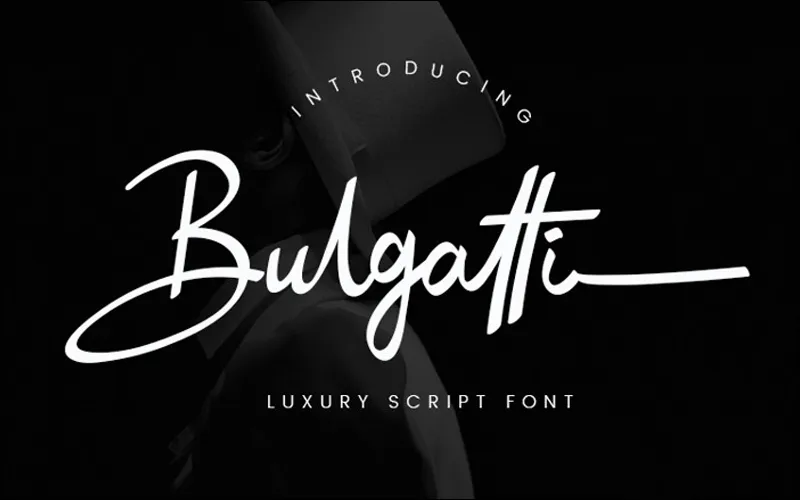
Bulgatti adalah font tegak bersambung kekinian dengan desain yang terlihat mahal. Font ini memiliki ukuran yang cukup tebal, sehingga cocok digunakan untuk membuat desain apa pun. Namun sangat cocok dipakai untuk membuat poster acara VIP.
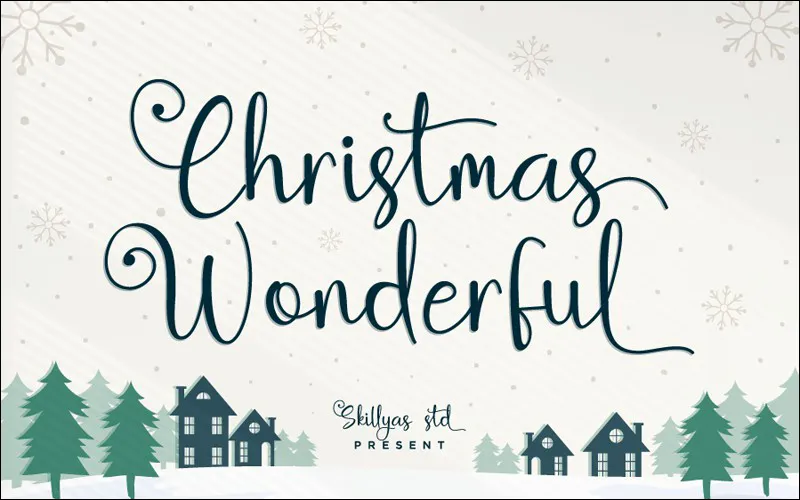
Sesuai dengan namanya, font Christmas Wonderful ini cocok dipilih untuk membuat desain bertema natal. Jadi kalau kamu ingin membuat kartu ucapan natal, poster, konten dan lainnya yang bertema natal disarankan menggunakan font Chrisftmas Wonderful ini.
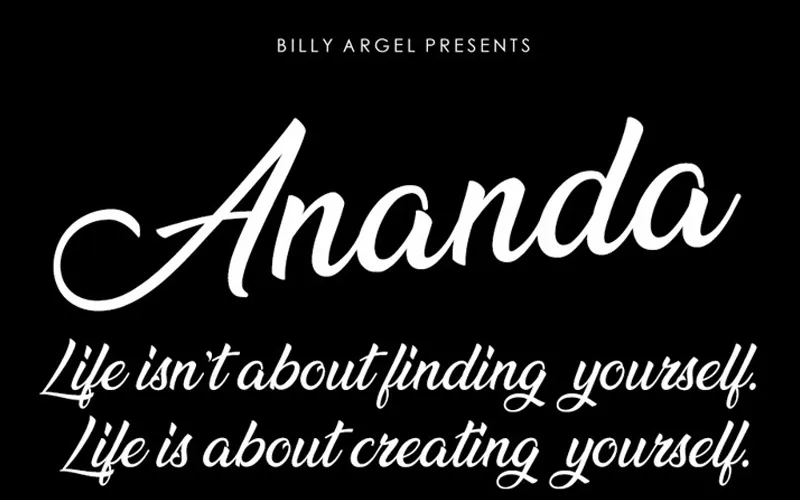
Ananda Black adalah font yang cocok Anda gunakan untuk membuat judul di dalam desain. Alasannya, karena font ini tidak terlalu terlihat menyambung, sehingga bisa mudah dibaca oleh orang lain yang melihatnya.
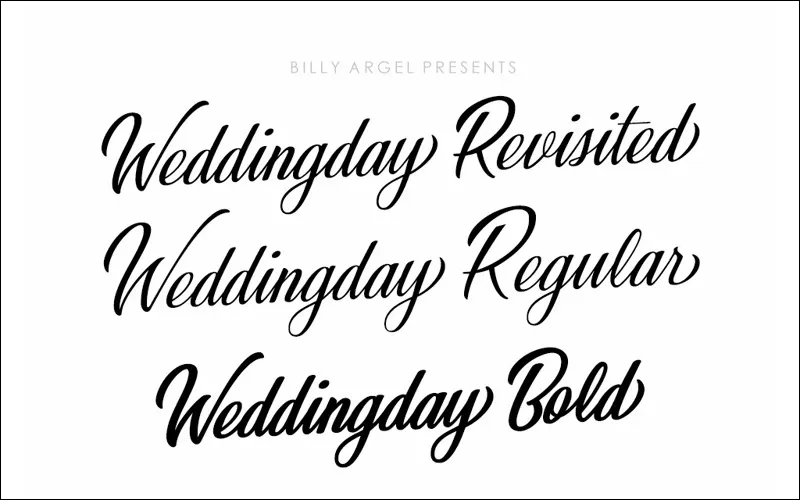
Undangan pernikahan biasanya menggunakan font tegak bersambung supaya terlihat cantik. Salah satu font tegak bersambung yang kami sarankan untuk desain tersebut adalah Wedding Day. Di mana font ini terlihat simpel, sehingga mudah untuk dibaca.
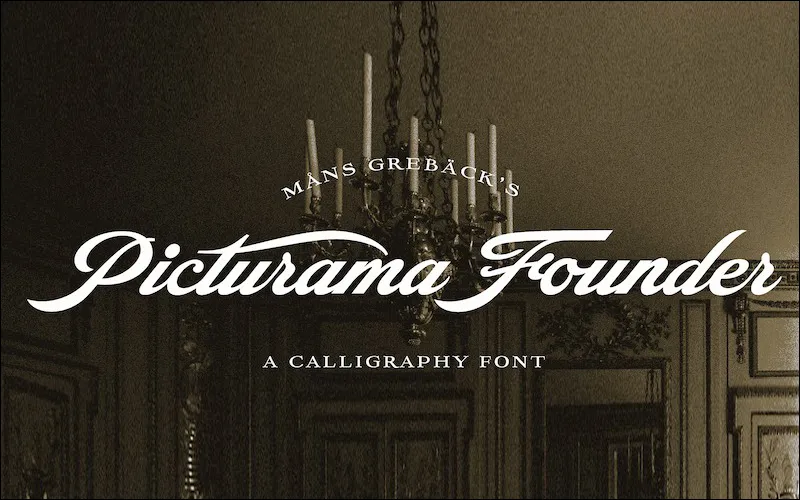
Picturama Founder merupakan salah satu font tegak bersambung yang terlihat mahal. Dari bentuknya yang miring, font ini bisa Anda gunakan untuk membuat desain logo aesthetic.
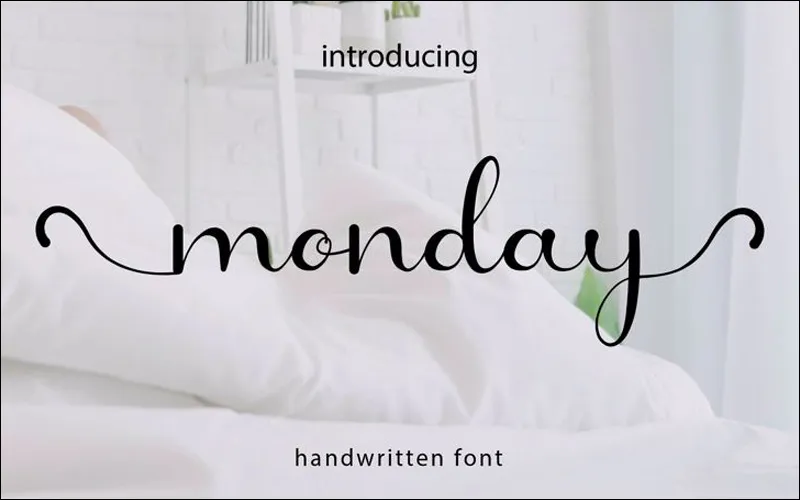
Bagi Anda seorang kreator, font Monday bisa menjadi pilihan untuk membuat desain kreatif. Umumnya, font ini sering dipilih oleh kreator perempuan, karena punya karakter yang cantik.
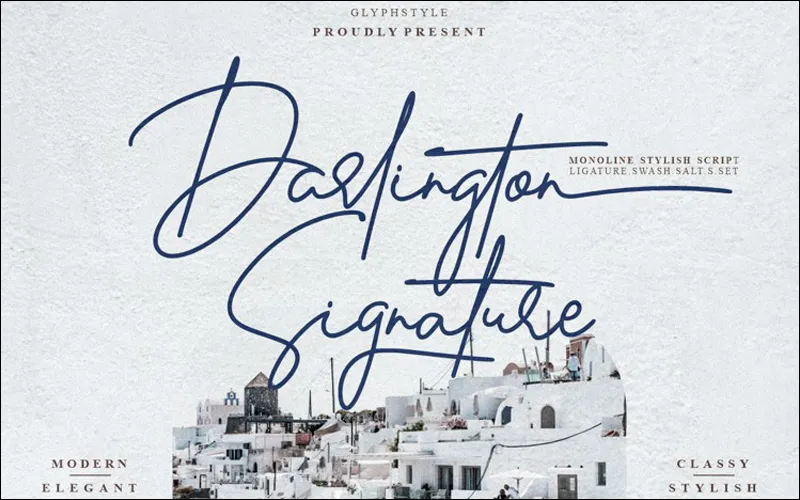
Sedangkan kalau Anda menyukai teks dengan bentuk mirip tanda tangan, maka bisa menggunakan Darlington Signature. Font ini memiliki karakter tipis dan kaku, mirip seperti tanda tangan.
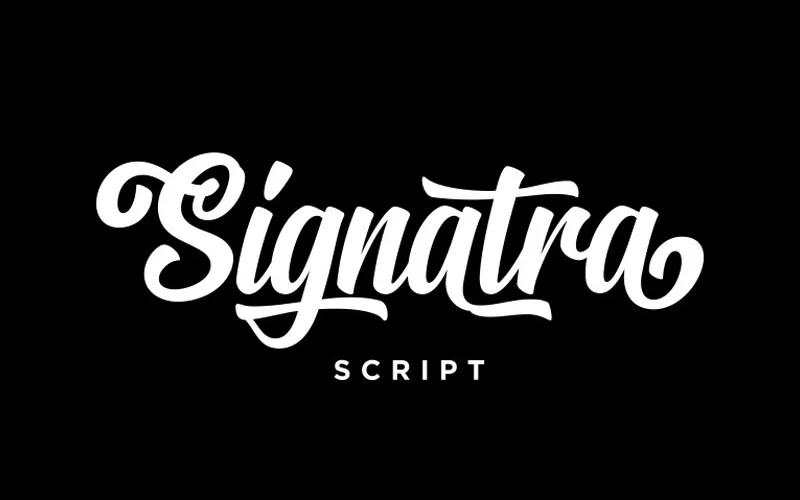
Sedangkan kalau ingin font tegak bersambung mirip tanda tangan namun punya karakter tebal, bisa pakai Signatra. Biasanya font ini sering dipakai juga untuk membuat judul di desain apa pun.
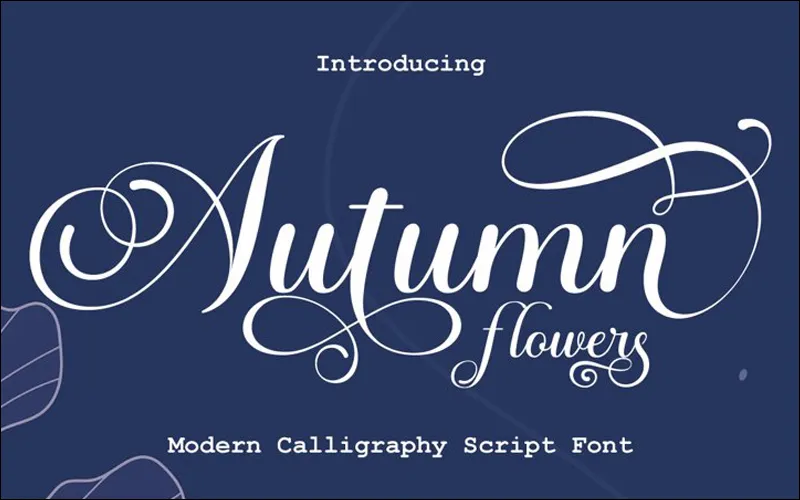
Autumn Flower adalah font tegak bersambung modern yang cukup sering digunakan untuk membuat beragam desain. Mulai dari desain undangan pernikahan, acara ulang tahun, poster kesenian dan sebagainya.
Emotional Rescue adalah font tegak bersambung yang punya desain kursif. Di mana, setiap karakter di font ini di desain menyambung dengan bentuk yang cenderung mengalir. Mirip seperti tulisan tangan.
Kalau kamu sedang membuat desain yang bertema keuangan, Billions Dream bisa menjadi pilihan. Font ini biasa dipakai untuk membuat judul buku finansial.
Stylish Calligraphy adalah font tegak bersambung yang mengusung tema kaligrafi. Font ini bisa digunakan untuk membuat desain apa pun. Lebih cantik lagi, jika Anda bisa memadukan warna yang pas.
Font undangan pernikahan sedang banyak dicari belakangan ini. Di tambah adanya undangan digital. Salah satu font untuk membuat desain undangan yang bisa Anda pilih adalah Geraldine. Bentuknya yang cantik, di tambah riasan bunga di beberapa karakter membuat font ini sangat direkomendasikan untuk dipilih.
Cherolina adalah font tegak bersambung yang punya indent panjang. Meskipun begitu, font ini punya desain yang elegan dan mewah sehingga cocok digunakan untuk membuat apa pun.
Font tegak bersambung untuk membuat judul selanjutnya adalah Majestic. Alasannya karena font ini punya ukuran besar dan tebal. Sehingga kalau Anda menggunakan font Majestic untuk membuat judul akan jadi lebih mudah terbaca.
Font bertema natal yang bisa Anda pilih lainnya adalah Christmas Wish Calligprahy. Menariknya dari font ini, terdapat karakter dengan simbol salju. Sehingga bisa mempercantik desain natal Anda.
Selanjutnya ada Millenia. Font yang kekinian ini biasanya dipakai oleh sekolah atau universitas untuk membuat desain kegiatan acara. Seperti acara kesenian, perlombaan dan musik.
Ada beberapa, seperti Millenia, Ananda Black, Emotional Rescue dan Black Mountain.
Anda bisa gunakan font Wedding Day, Autumn Flower, Geraldine, Widie Gusti dan Stolen Times.